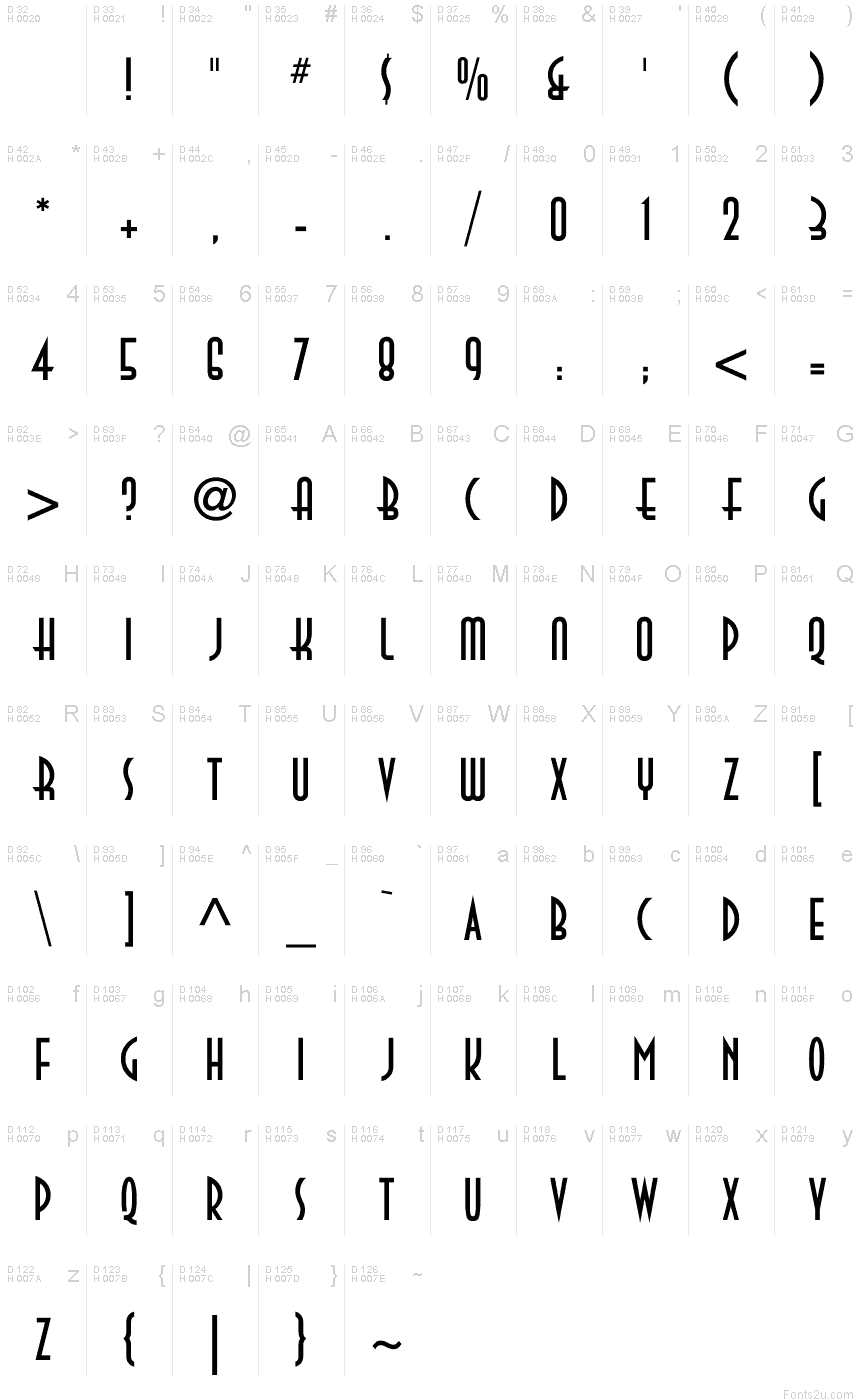
DecoTech TL
DecoTech TL to darmowy krój display w stylu retro, który emanuje czystym splendorem Art Déco w nowoczesnym wydaniu. Wysokie, wąskie litery, mocne linie pionowe i eleganckie geometryczne krzywizny przywodzą na myśl szyldy starych kin i luksusowych hoteli. Wyrazisty rytm i ciasne światła między znakami sprawiają, że rodzina DecoTech pozwala tworzyć efektowne, plakatowe napisy, które łączą w sobie nostalgię z nowoczesnym sznytem.
Ten darmowy font DecoTech TL doskonale sprawdza się na plakatach eventowych, w luksusowym brandingu, na opakowaniach, okładkach książek, w systemach identyfikacji wizualnej czy odważnych logotypach. Jego rzeźbiarskie formy najlepiej wyglądają w dużych rozmiarach, gdzie dramatyczne sylwetki liter mogą w pełni wybrzmieć; dodaj do tego prosty, dyskretny krój bezszeryfowy do tekstu głównego, a uzyskasz kompletny zestaw w klimacie vintage.